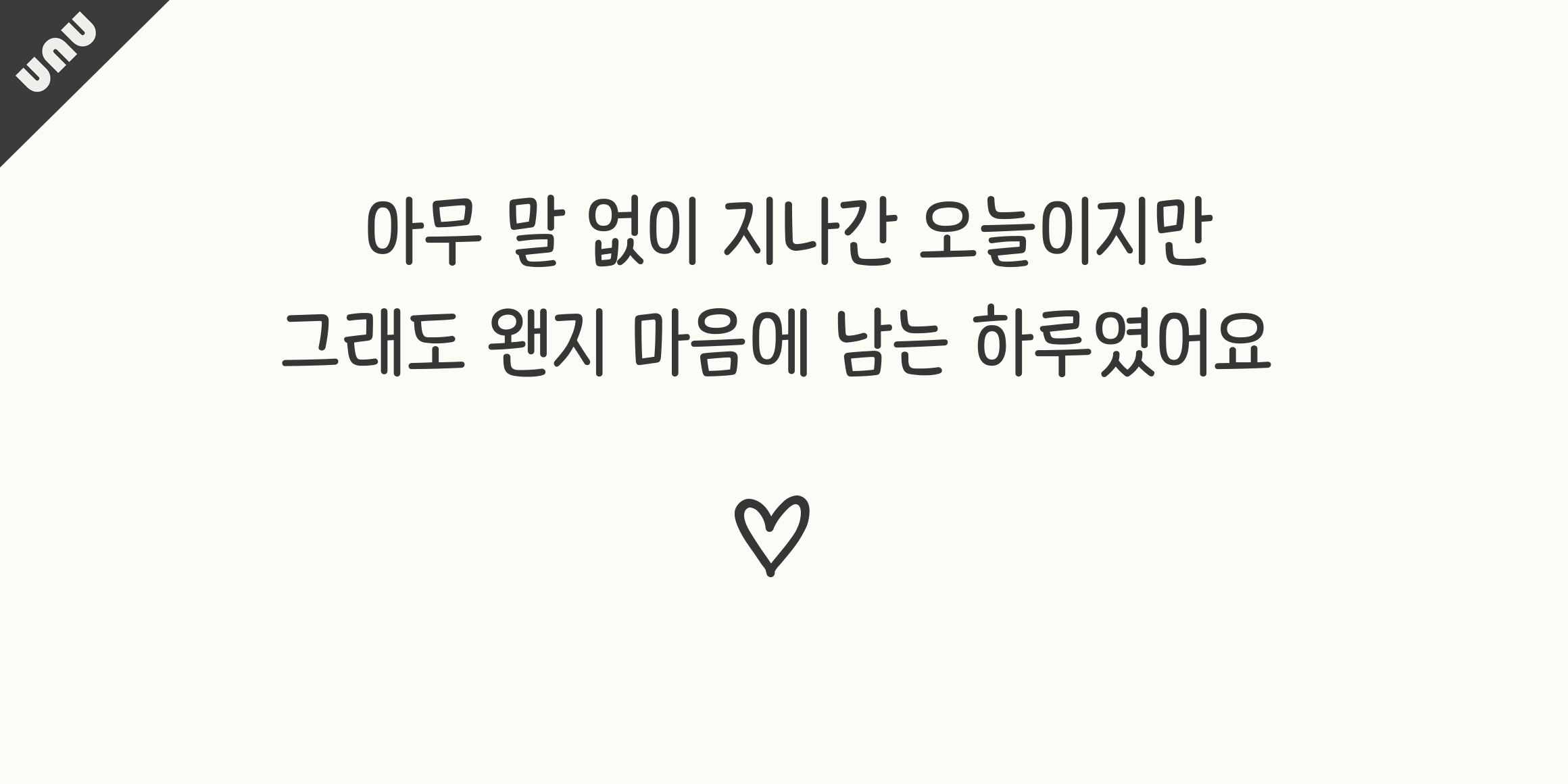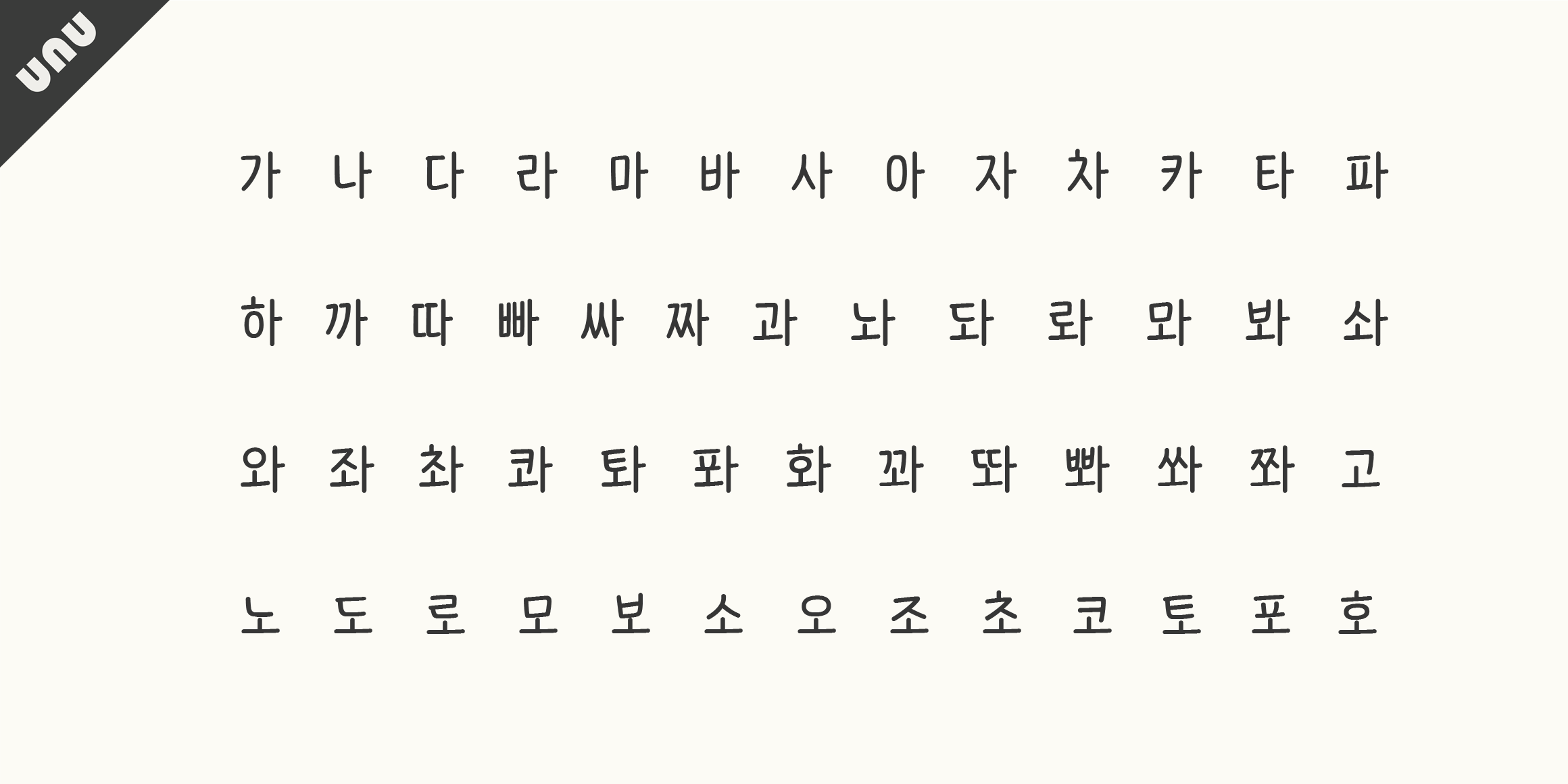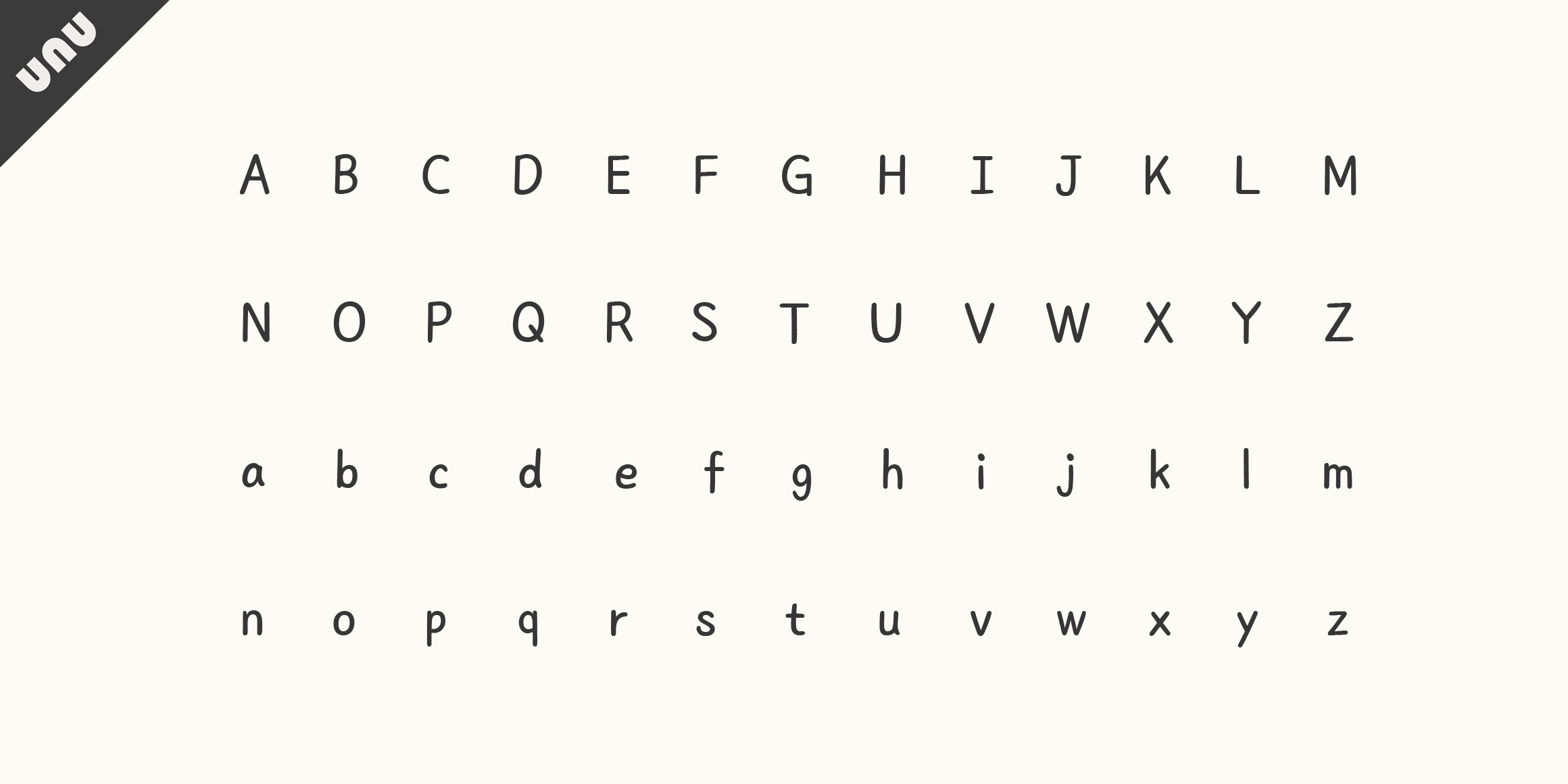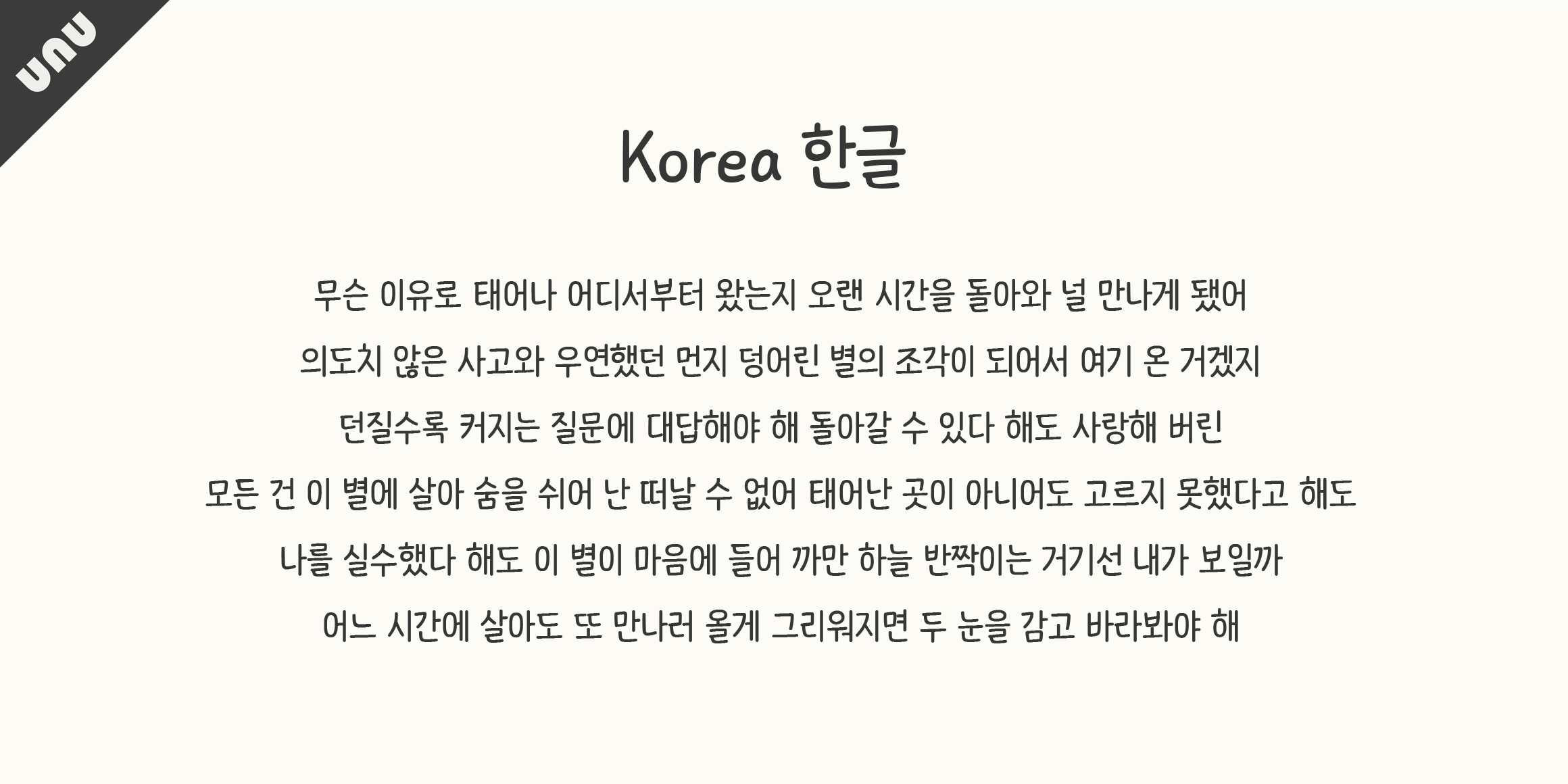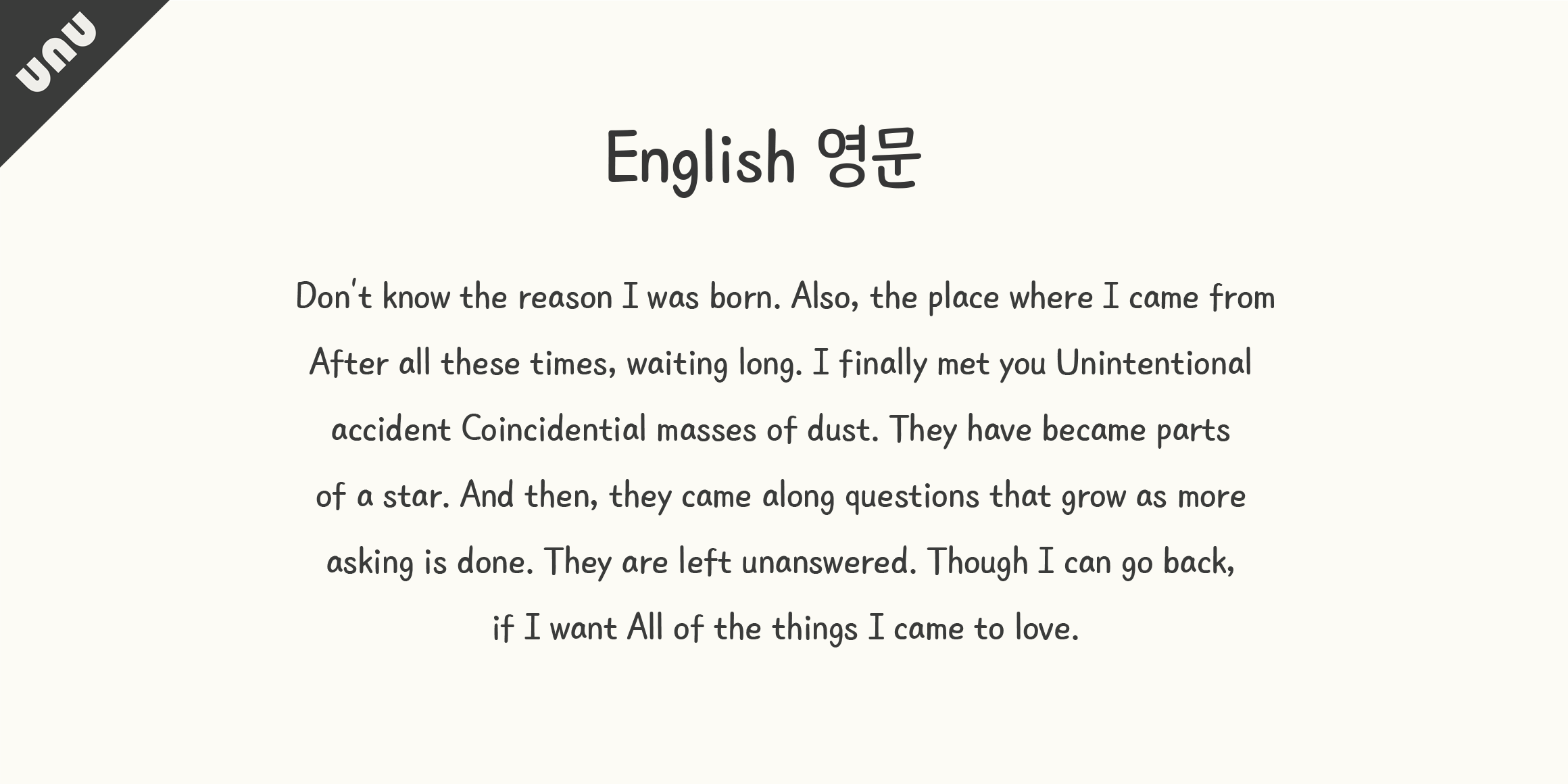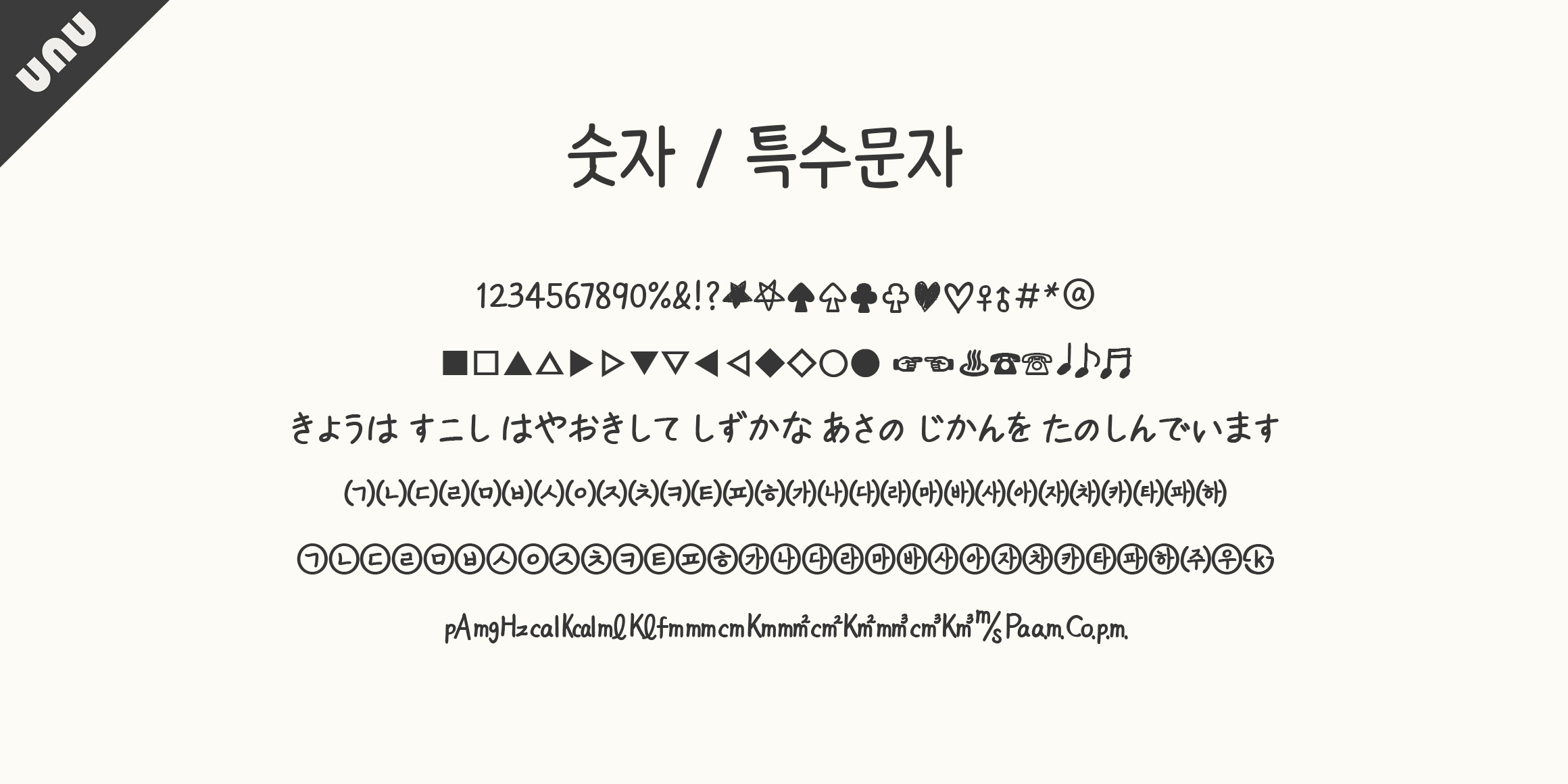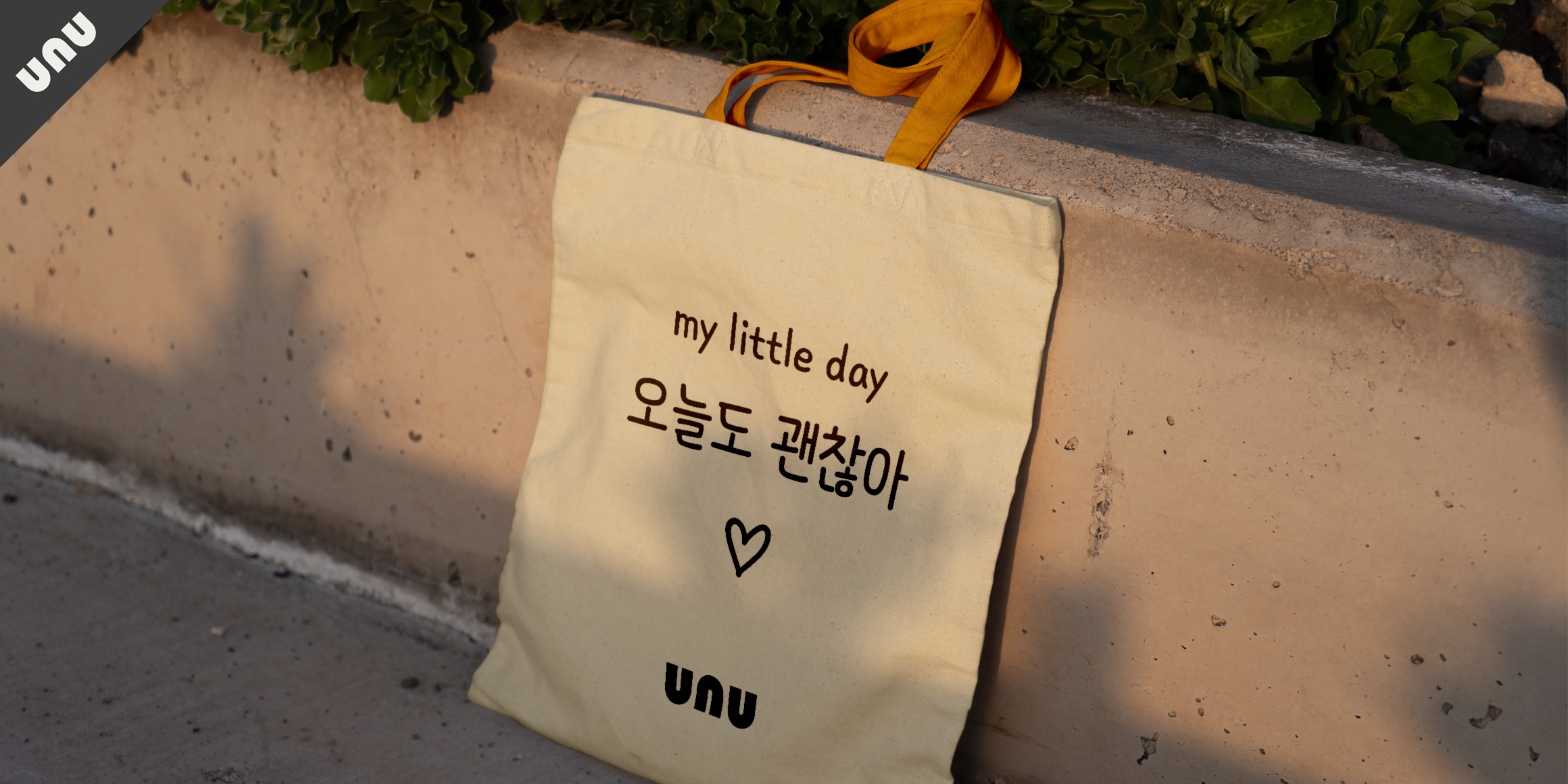
unu 손고딕더볼드
이 서체는 유앤유타입의 손고딕의 조금더 볼드한 버전으로 단정하고 바른 느낌의 손으로 쓴 고딕서체 컨셉의 서체이다. 사랑하는 누군가에게 따뜻한 마음을 전하고 싶을때, 내 소중한 다이어리에 오늘을 기록하고 싶을때 추천드립니다. 유앤유서체는 당신의 따뜻한 마음을 전해드립니다.
• unu 손고딕더볼드 / unu HandGothicbold